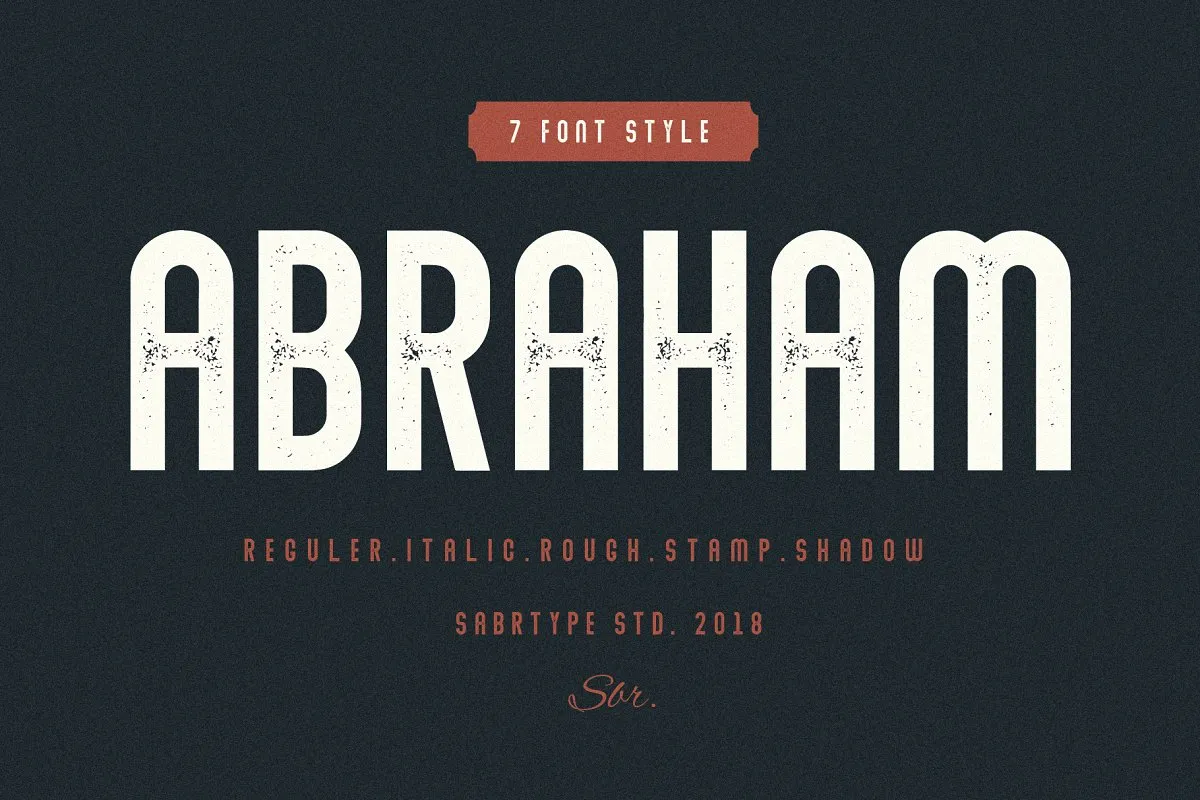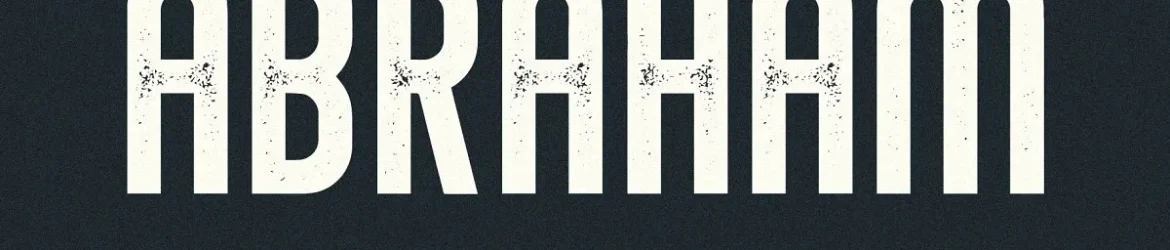
Introduzimos a família Abraão de fontes tipoface. Este é um famoso família moderna de sans-serif modular, baseada em fontes sólidas. Abraão combina diversos estilos como Regular, Italic, Rough, Stamp e Shdow. É ideal para logotipos, cartões de agradecimento, citações, panfletos, marca, cartões de visita, papel de parede, títulos de design, cabeçalhos de blog, declarações artísticas e tipografia. Seja você um designer ou um artista digitado, Abraão é uma escolha perfeita. O estilo moderno e modular da família pode adaptá-la para muitos usos. Seja um projeto gráfico que precisa ser chamativo como cartões de visita, panfletos ou logotipos de marca. Ou se você estiver criando algo mais artístico, Abraão é uma ótima fonte para cabeçalhos de blog e artigos de declarações. Não espere mais, experimente a família de fontes Abraão hoje! Combinada com sua facilidade de uso e estilos variados, certamente irá adorar seu uso.